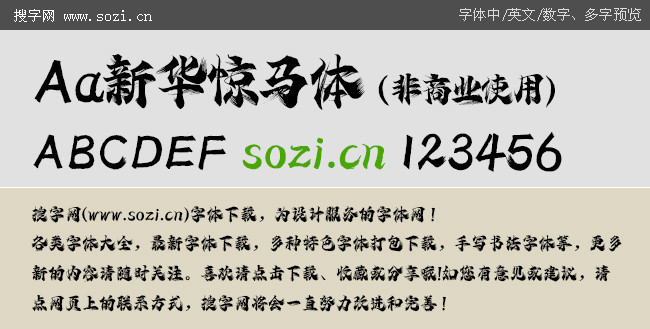
Aa新華驚馬體
搜字網(wǎng)給大家提供一款A(yù)a新華驚馬體(非商業(yè)使用)中文字體下載,該字體是一款手寫(xiě)字體,字體書(shū)寫(xiě)流暢,字形隨性灑脫,具有很好的視覺(jué)感,適用于平面宣傳設(shè)計(jì)、網(wǎng)頁(yè)設(shè)計(jì)、海報(bào)設(shè)計(jì)等應(yīng)用(此字體為個(gè)人非商用版,商用可以聯(lián)系QQ:1006760504)。
- 風(fēng)格類別: 手寫(xiě)書(shū)法體